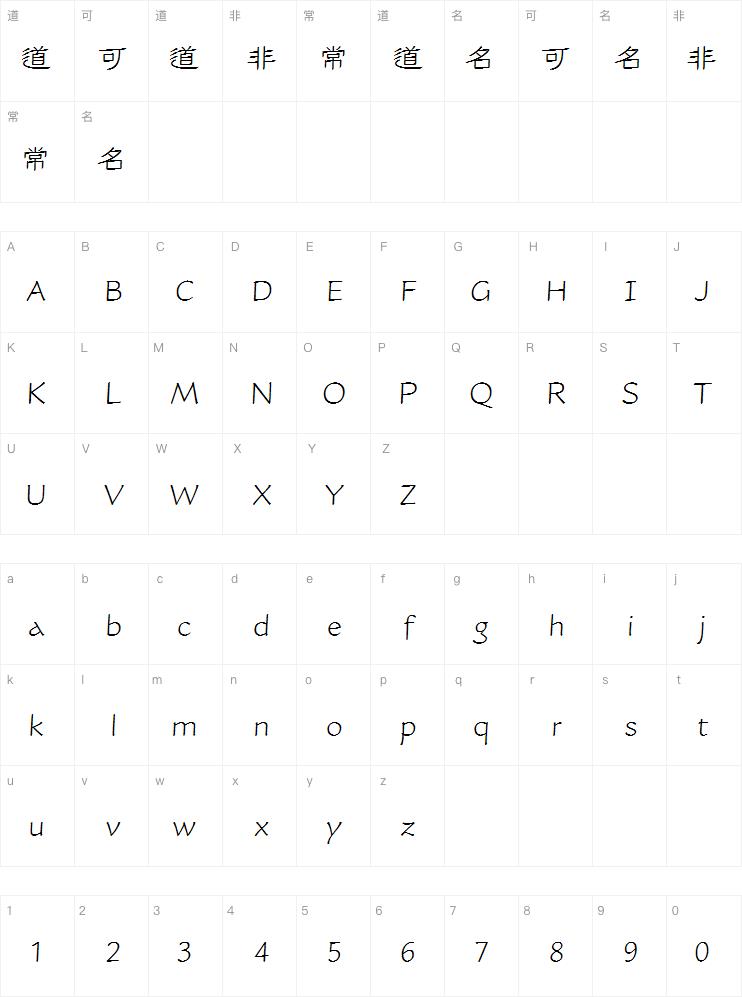
汉仪汉源墨隶45f
汉仪汉源墨隶是一款融合传统隶书笔意与现代设计美学的字体。其字形以经典隶书为根基,保留蚕头燕尾、横平竖直的典型特征,同时融入书法墨迹的自然韵律感,笔画边缘呈现微妙的飞白与枯笔痕迹,模拟宣纸书写的苍劲质感。整体风格古朴厚重又不失灵动,既彰显汉字文化的典雅韵味,又适应现代视觉审美需求。 该字体适用于文化类海报、古籍排版、品牌logo设计等场景,尤其擅长表现传统主题内容,能在传递历史感的同时保持清晰可读性,是兼具艺术性与实用性的设计佳选。
汉仪汉源墨隶45f